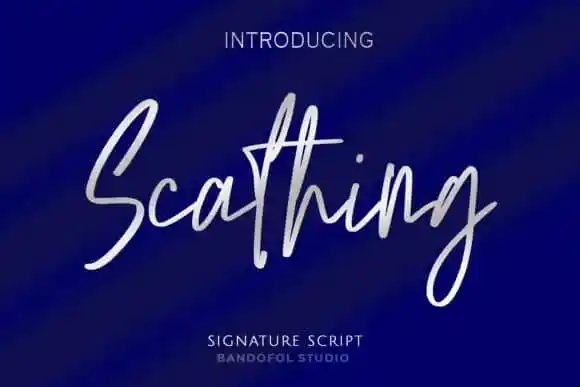
A fonte ‘Scathing Handwritten Font’ é uma escolha perfeita para quem busca uma fonte elegante e divertida que destaca qualquer projeto criado com ela. Desenvolvida pela Bandofol Studio, essa fonte possui um estilo de assinatura manuscrita elaborada, adornos charmosos e uma base vertical em movimento leve. Ela é perfeita para aquelas criações que desejam um ar descontraído e desequilibrado, sem perder o brilho sofisticado e elegante da sua escrita. Uma excelente opção para designers buscando dar vida a seus projetos de uma maneira única, ‘Scathing Handwritten Font’ se adapta perfeitamente tanto para aplicativos digitais quanto impressões em papel, oferecendo um charme autêntico que certamente irá destacar sua produção.